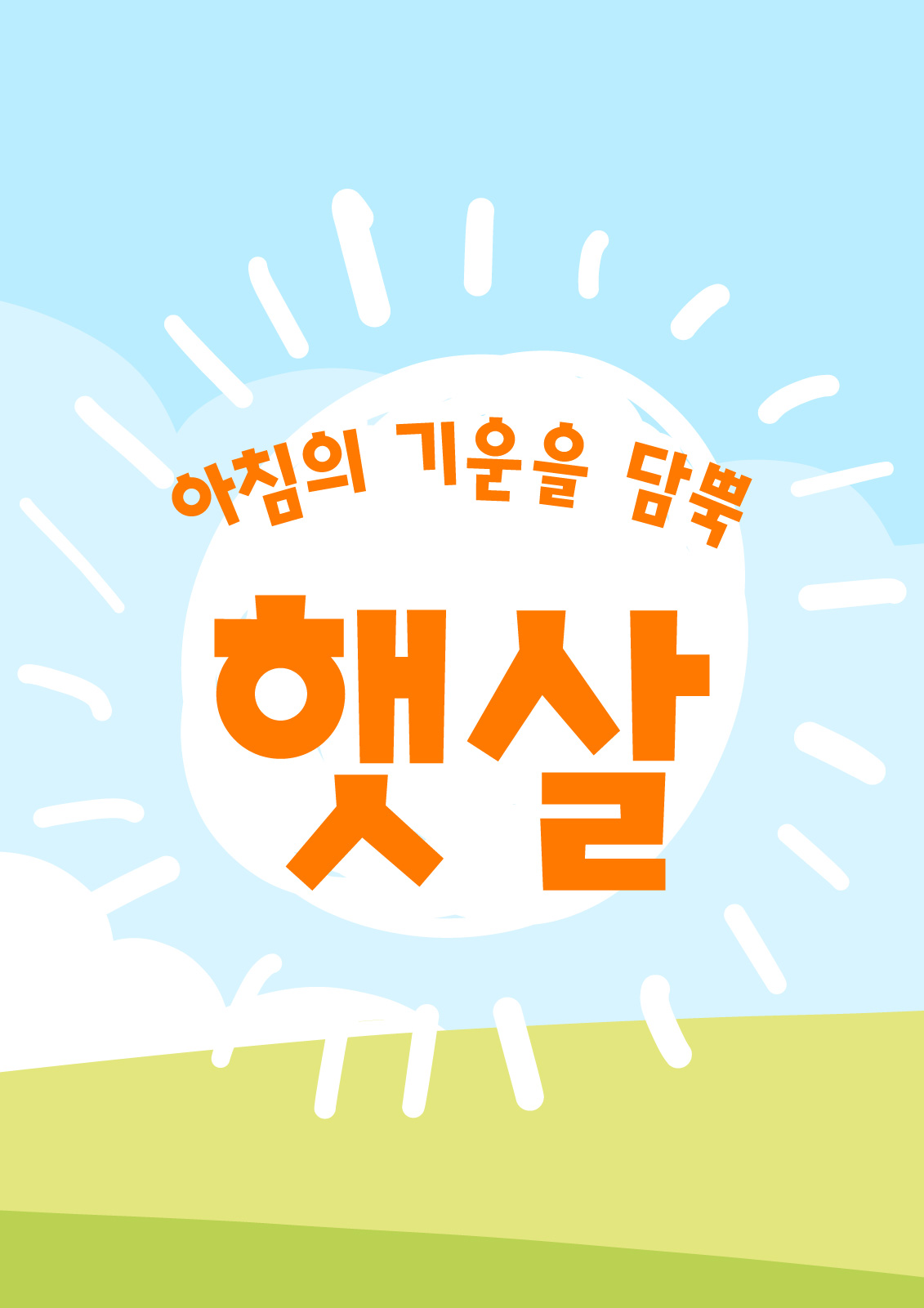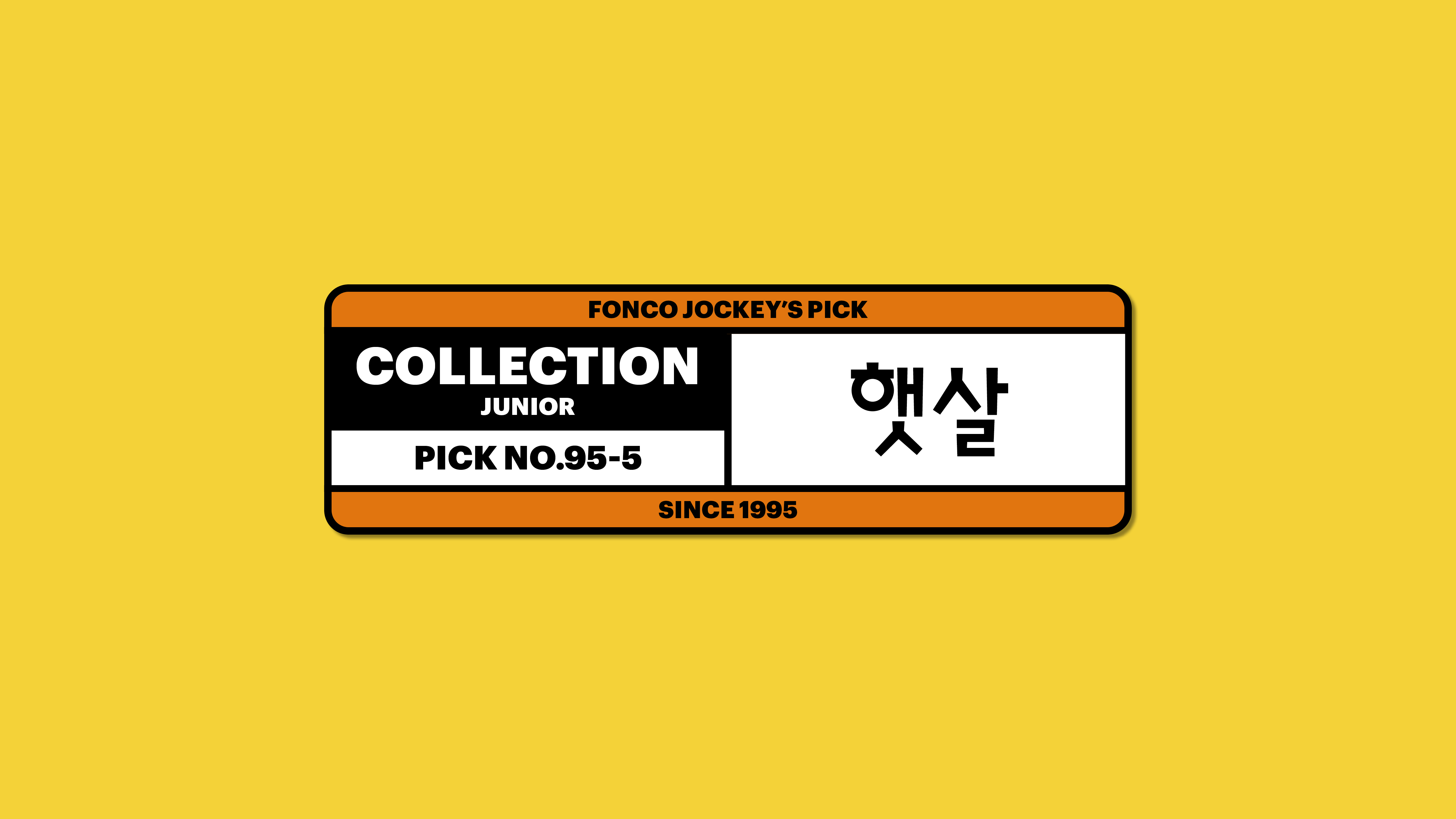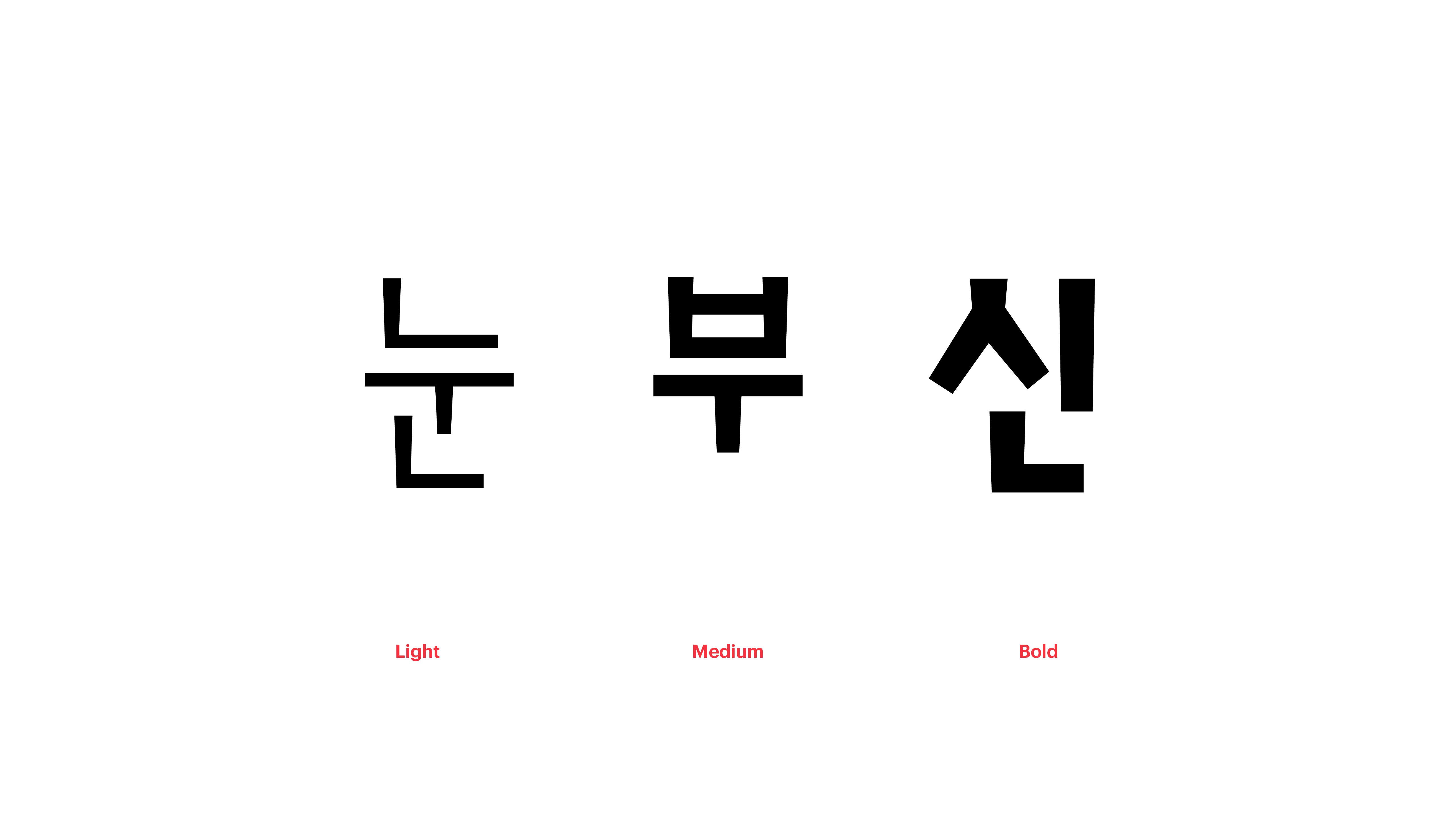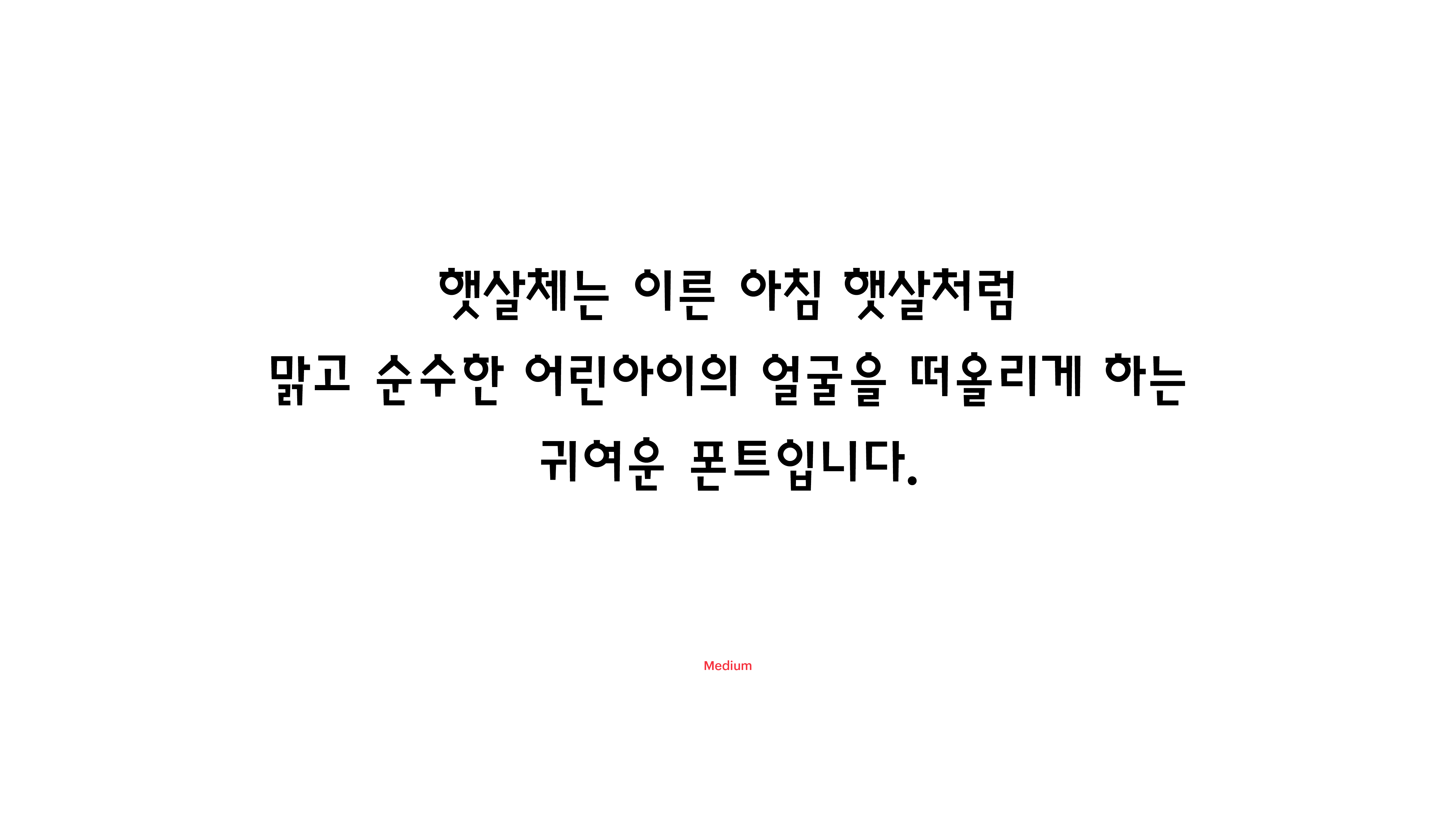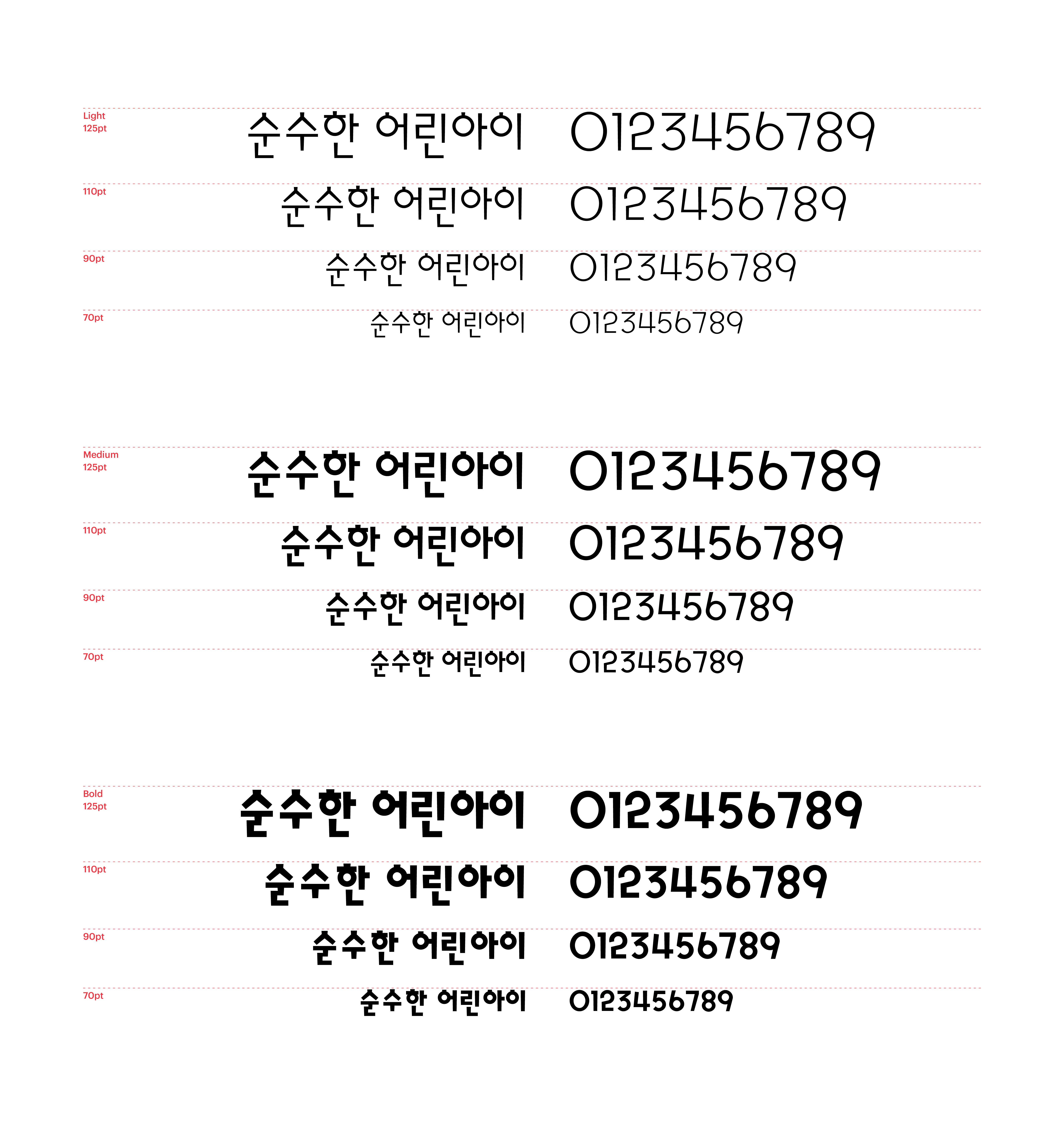
햇살을 받으며 거리를 걸으면 마음이 한없이 순해지는 기분이 듭니다. 그때 우리의 표정, 햇살체의 생김새와 닮지 않았나요? 햇살체는 이른 아침 햇살처럼 맑고 순수한 어린아이의 얼굴을 떠올리게 하는 귀여운 폰트입니다. 글자 하나, 하나. 각기 다른 표정을 그려 넣듯, 글자마다 폭과 길이를 다르게 조정해 올망졸망한 감성을 연출하였답니다.
Yoon 햇살